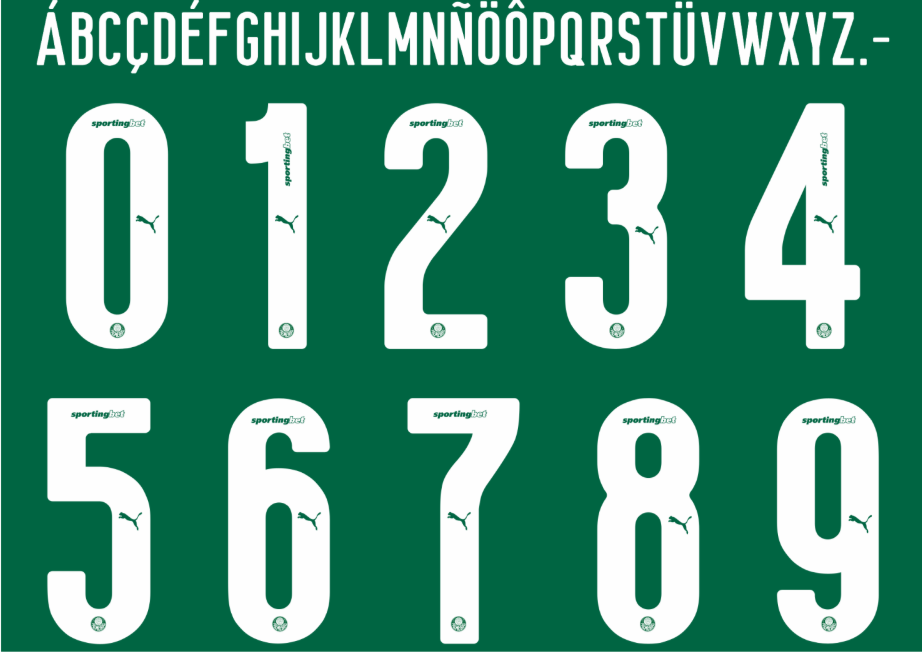
O Verdão entra em campo para mais uma temporada de conquistas e a Puma mais uma vez inova na identidade visual do Alviverde Imponente. Para a temporada 2026/2027, a camisa do Palmeiras traz uma tipografia que une a tradição da Academia de Futebol com o design agressivo e moderno exigido pelo futebol atual.
Estilo Visual da Tipografia
A fonte desenvolvida pela Puma para o ciclo 2026/27 do Palmeiras reflete dinamismo e solidez. Abandonando as curvas mais suaves de temporadas passadas, o novo estilo aposta em traços retilíneos e cortes diagonais, inspirados na arquitetura do Allianz Parque e na modernidade da marca alemã.
Os números possuem uma leitura clara e imponente, ideal para a visibilidade em campo, enquanto as letras trazem uma estética “tech”, alinhada com as tendências globais de sportswear. É a escolha perfeita para quem busca replicar o visual oficial dos jogadores do elenco atual.